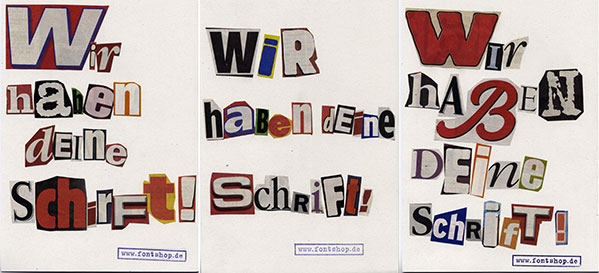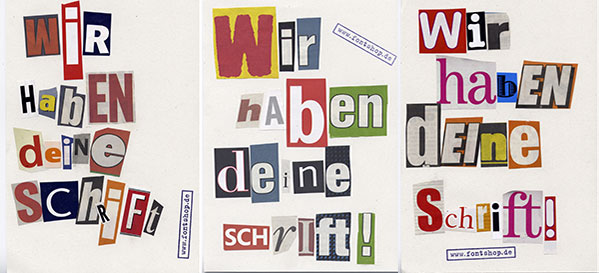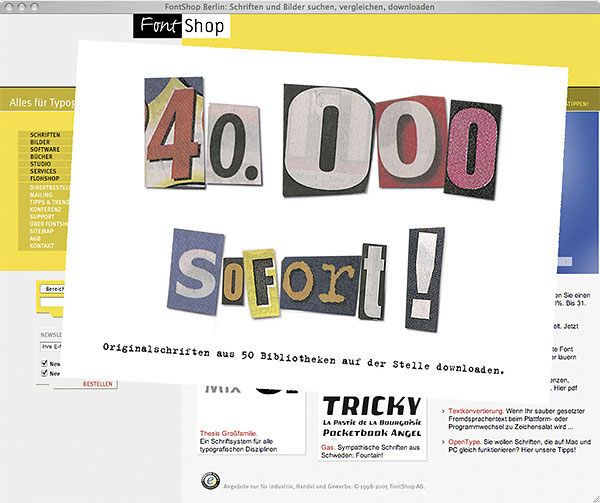
Kidnapping auf der BuchmesseErpresserschreiben beunruhigen seit heute morgen Aussteller und Besucher
der Frankfurter Buchmesse. »Wir haben deine Schrift!« steht in
ausgeschnittenen Lettern auf grauem Papier geschrieben. Darunter ein
Absenderstempel: www.fontshop.de. Geht man auf diese Webseite,
begrüßt den Besucher eine zweite Nachricht: »40.000
sofort!« Eine gehackte Website? Ein dummer Scherz? Was ist hier los?
![]() Alles in Ordnung. Nur ein bisschen Werbung für die Vielfalt der
Schrift. FontShop ist der Ansicht, dass viel zu viele Bücher und
Zeitschriften mit den immer gleichen Schriften gestaltet werden. Dabei gibt es
so viele, schöne Schriftfamilien. Und so haben wir uns vorgenommen, auf der
Frankfurter Buchmesse für die Mannigfaltigkeit der Schrift zu
werben.
Bei der Realisierung der Aktion half uns die Hamburger Werbeagentur Jung von Matt/Elbe – man nennt sie auch die »kreativste Agentur Deutschlands« (kein glücklicher Begriff, aber in der Werbung hält er sich beständig). Unser Briefing: eine temporäre, medienübergreifende Aktion, die Aufmerksamkeit erregt. Sie sollte Guerilla-Charakter haben, die Vielfalt der Schrift in der Kommunikation spielerisch transportieren und neugierig machen. Die Realisation: Nach wenigen Tagen präsentierte uns JvM dieses Flugblatt: ![]() Das »offizielle«, gedruckte Flugblatt (Auflage 5000 Exemplare) Die FontShop Marketing-Abteilung war begeistert und entwickelte die Idee mit JvM weiter. Die Auflösung des Erpresserbriefes soll die FontShop-Webseite liefern. Kidnapper haben sie scheinbar gehackt ... mit einer Auflösungsbotschaft. Die war schnell gefunden: ![]() Eine Entführerbotschaft überlagert die FontShop-Homepage für die Dauer der Frankfurter Buchmesse und zwei Tage danach Die Verantwortlichen bei JvM: Text: Peter Kirchhoff AD: Kay Potthoff Grafik: Patrik Hartmann Produktion: Jörg Mergemeier Beratung: Guido Kirschner FontShop bestand darauf, dass es neben dem gedruckten Schreiben eine größere Menge handgemachter Originale geben muss, die ebenfalls auf der Buchmesse verteilt werden sollen: entweder an ganz bestimmte Personen oder an ausgesuchte Lokalitäten (zum Beispiel ein Toilettenspiegel im Pressezentrum). Bald brach das Bastelfieber im Büro aus. Die Marketing-Abteilung richtete eine Arbeitsplatz mit allen notwendigen Accessoires ein: Blankopapier (ausgesucht von JvM), Schere, Klebstoff, Gitterkörbchen zum Sortieren und täglich eine BILD-Zeitung. ![]() Der »Erpresser-Arbeitsplatz« im FontShop: täglich eine BILD-Zeitung ergab 5 handgeklebte Originale ![]() ![]() Wenn Sie auf der Buchmesse eines dieser Originale finden, können Sie Stolz sein! Reportage von der Buchmesse: Tag 1 morgens Tag 1 mittags Tag 1 abends Herausgegeben: Do - Oktober 20, 2005 at 12:45 vorm. | |